「おしゃれなフォントを使いたいけど、種類が多すぎて選べない」
「無料で使えて、商用利用できるフォントを知りたい」
そんな方に向けて、本記事では“見た目がおしゃれ”なだけではなく、実際のデザイン現場でも使いやすい無料フォントを厳選して紹介します。
最近では、YouTubeサムネイル、Instagram投稿、VTuber配信、ブログ、ロゴ制作、カフェメニュー、ショップカードなど、フォント選びがデザイン全体の印象を左右する場面が増えています。
しかし、無料フォントには「商用利用NG」「漢字が少ない」「英数字しか対応していない」など、実際に使う際の注意点も少なくありません。
そこで本記事では、日本語対応・商用利用可否・おすすめ用途・デザインの雰囲気までわかりやすく整理しながら、おしゃれフォントをカテゴリ別にまとめました。
「結局どれを選べばいいかわからない」という方でも、自分に合ったフォントを見つけやすい構成になっているので、ぜひ最後までチェックしてみてください。
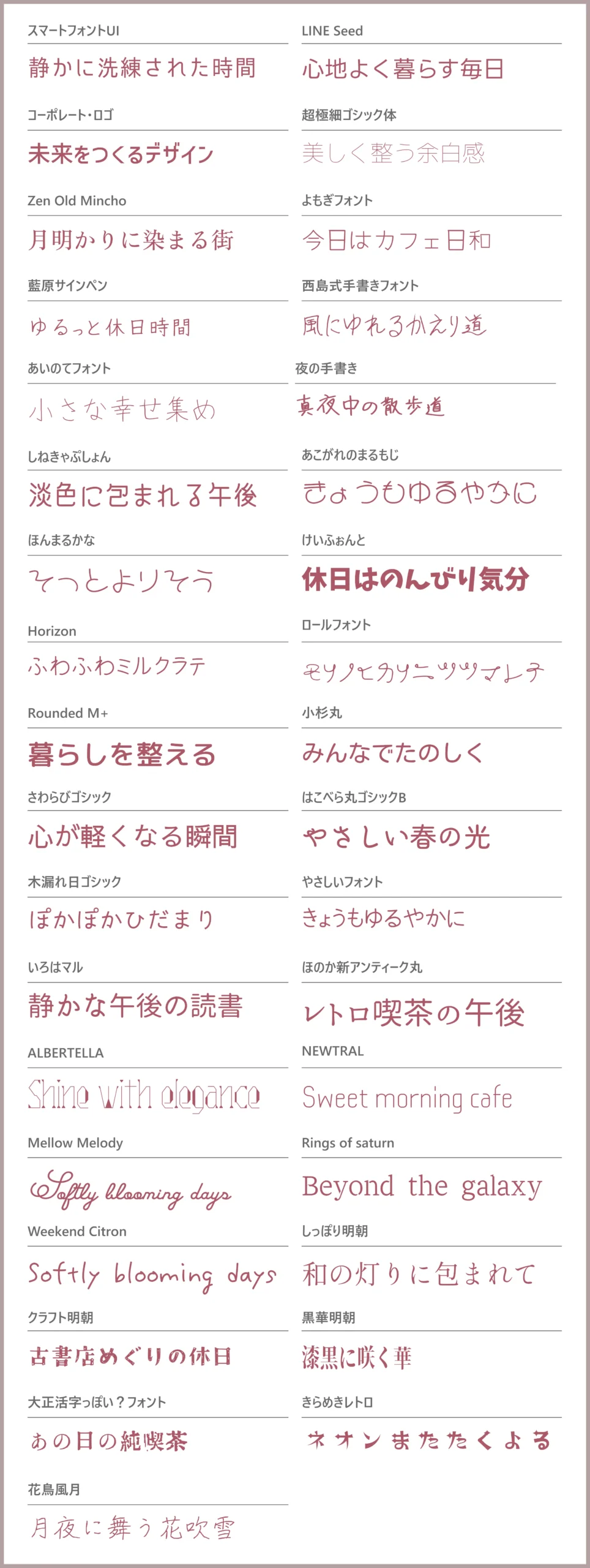
おしゃれフォントとは?
おしゃれフォントとは、単に文字を読むためだけではなく、“世界観や雰囲気を演出するため”に使われるデザイン性の高いフォントのことです。
同じ文章でも、フォントが変わるだけで「高級感」「かわいさ」「レトロ感」「近未来感」など、受ける印象は大きく変化します。
特に最近では、SNS投稿・動画サムネイル・ロゴ制作など、第一印象が重要なデザインでおしゃれフォントが多く活用されています。
ここでは、まず「おしゃれフォントとは何か」「普通のフォントと何が違うのか」をわかりやすく解説します。
おしゃれフォントの特徴
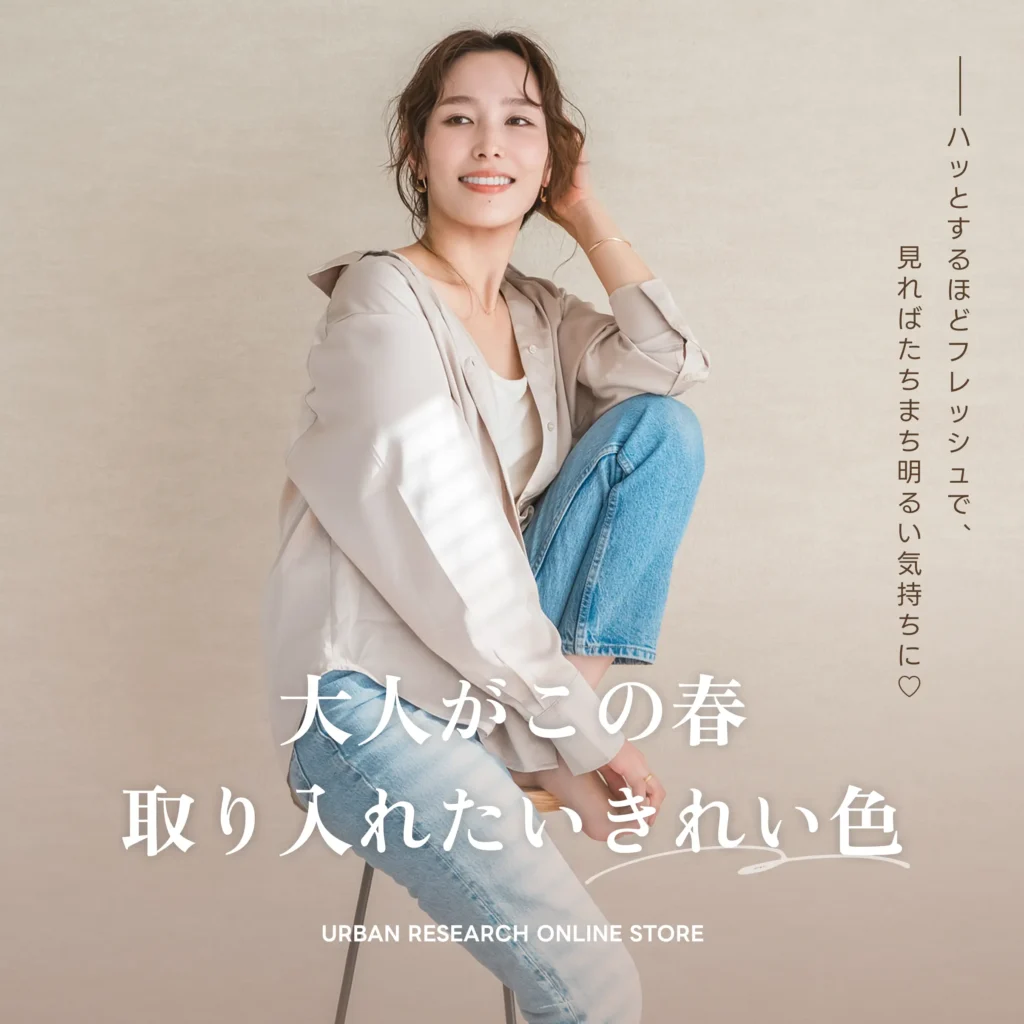
おしゃれフォントには、一般的な標準フォントにはない“デザイン性”があります。
例えば、線の太さに強弱があったり、文字の角が丸く設計されていたり、独特な余白バランスになっていたりと、文字そのものがデザインの一部として機能するのが特徴です。
特に以下のような特徴を持つフォントは、「おしゃれ」と感じられやすい傾向があります。
- 余白が美しい
- シルエットに個性がある
- 手書き感や筆記感がある
- ブランド感を演出しやすい
- 写真や動画と馴染みやすい
最近では、韓国風デザイン・Y2K・ミニマルデザインなど、トレンド系デザインでもフォントの重要性が高まっています。
普通のフォントとの違い
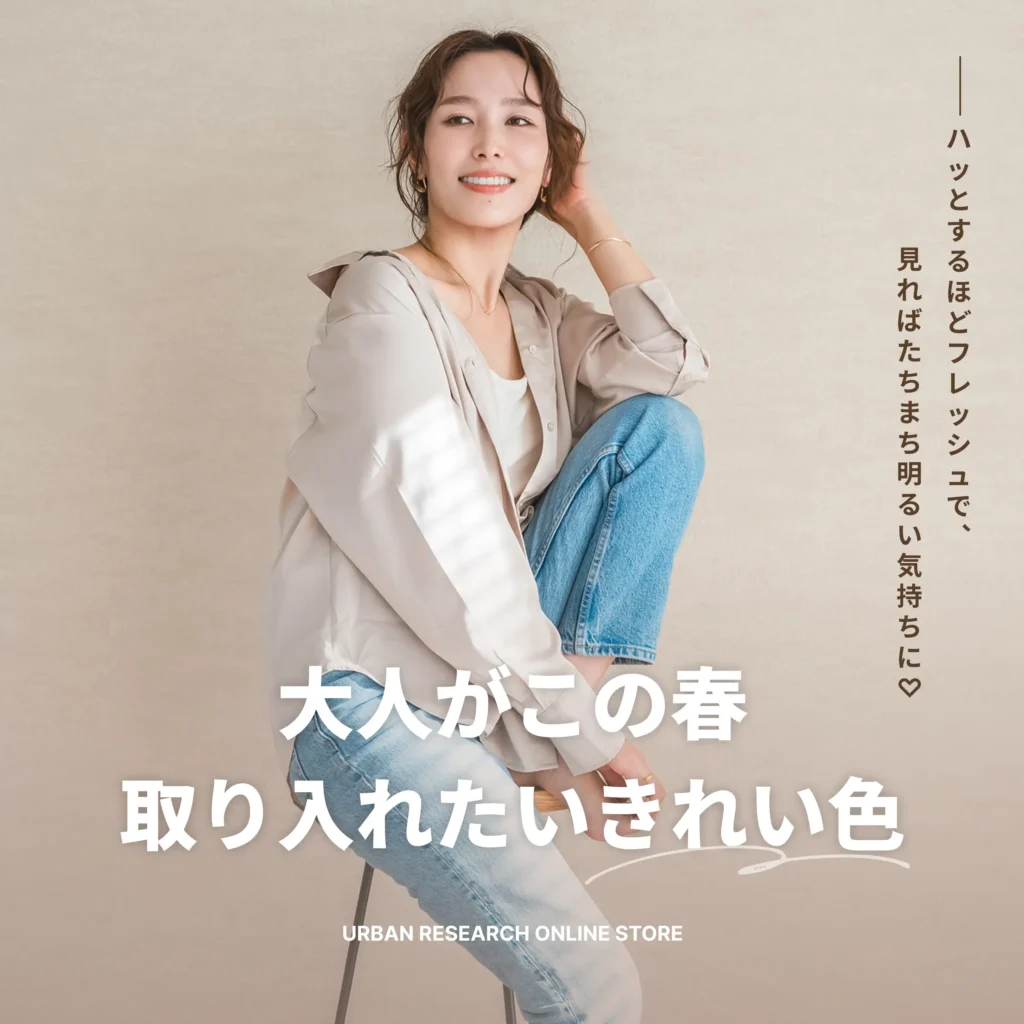
一般的なフォントは「読みやすさ」を重視して作られています。
一方、おしゃれフォントは“見せること”を目的として設計されているものが多く、文字自体がデザインのアクセントになります。
例えば、Wordの標準フォントは長文でも読みやすいように設計されていますが、おしゃれフォントはタイトルやロゴなど、印象を強く残したい場面で使われるケースが中心です。
そのため、
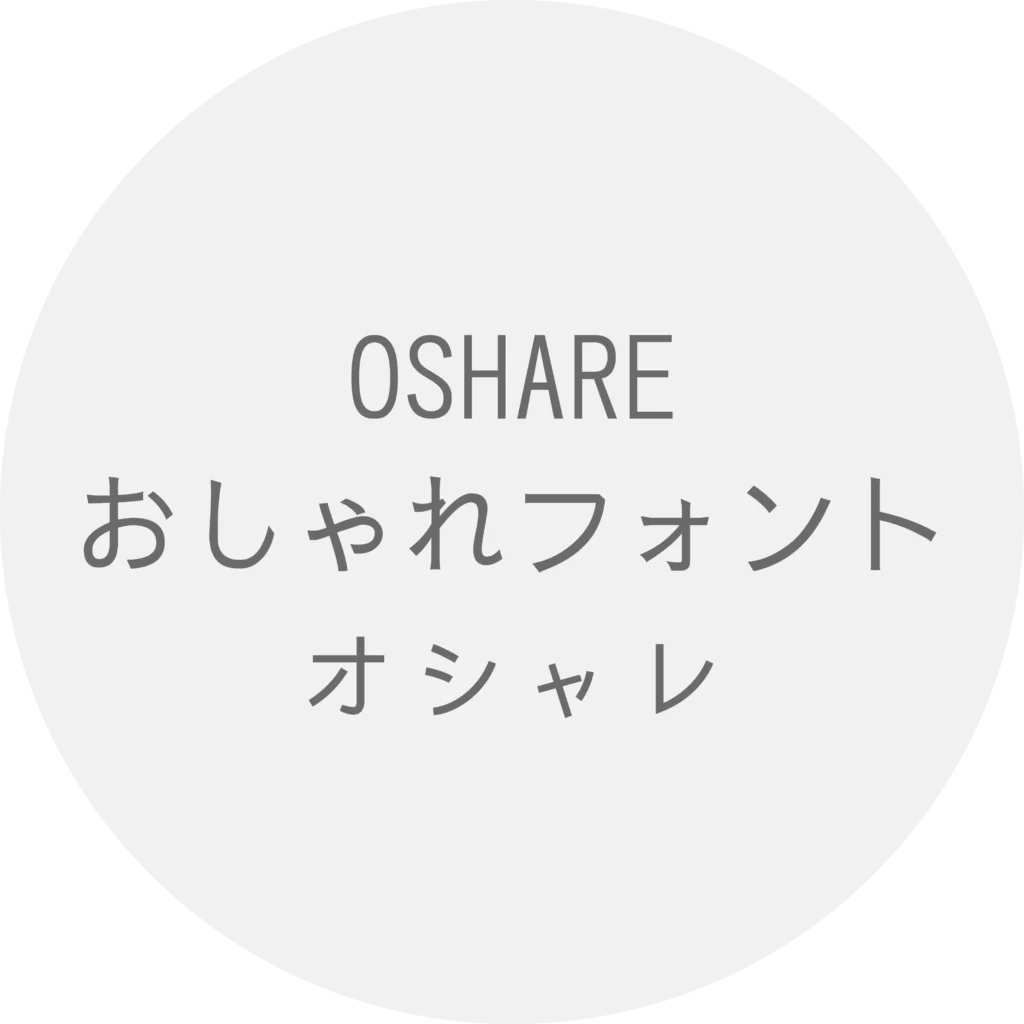
可読性重視
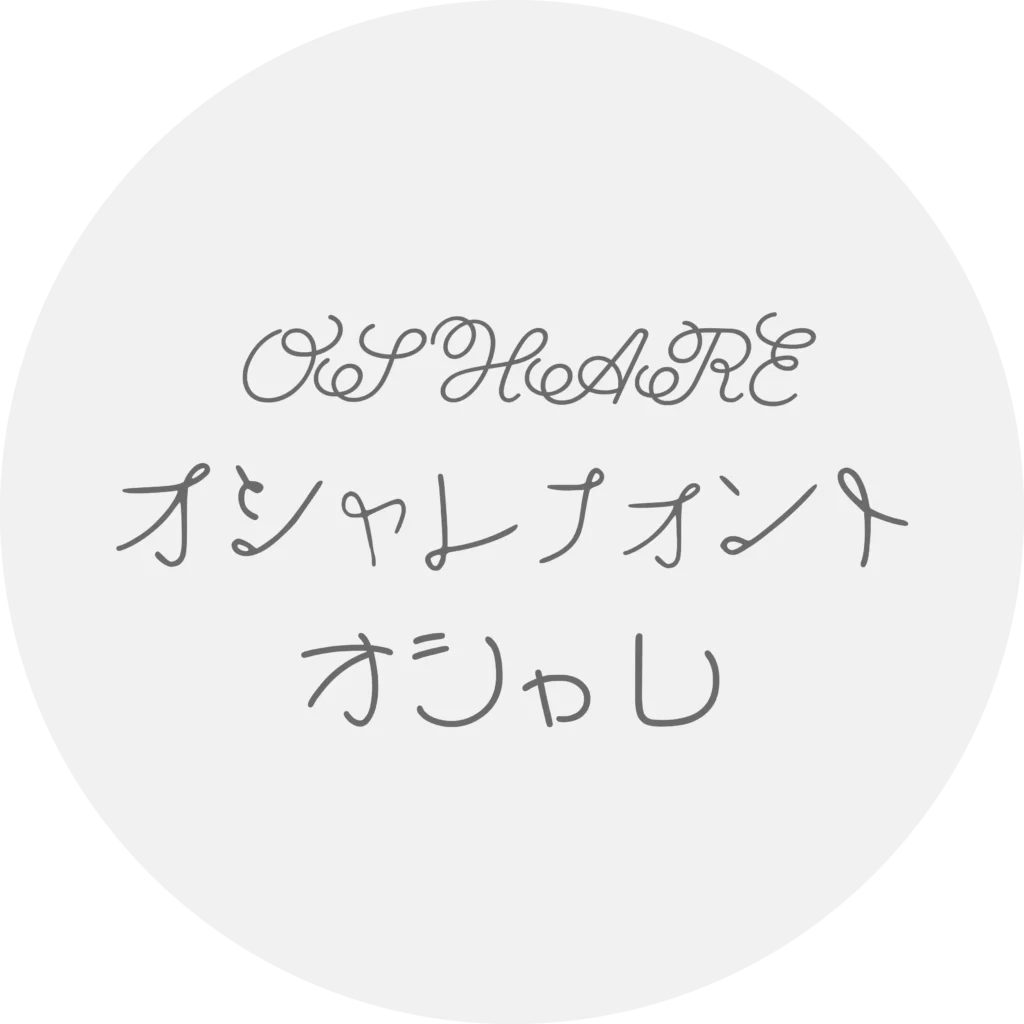
装飾性重視
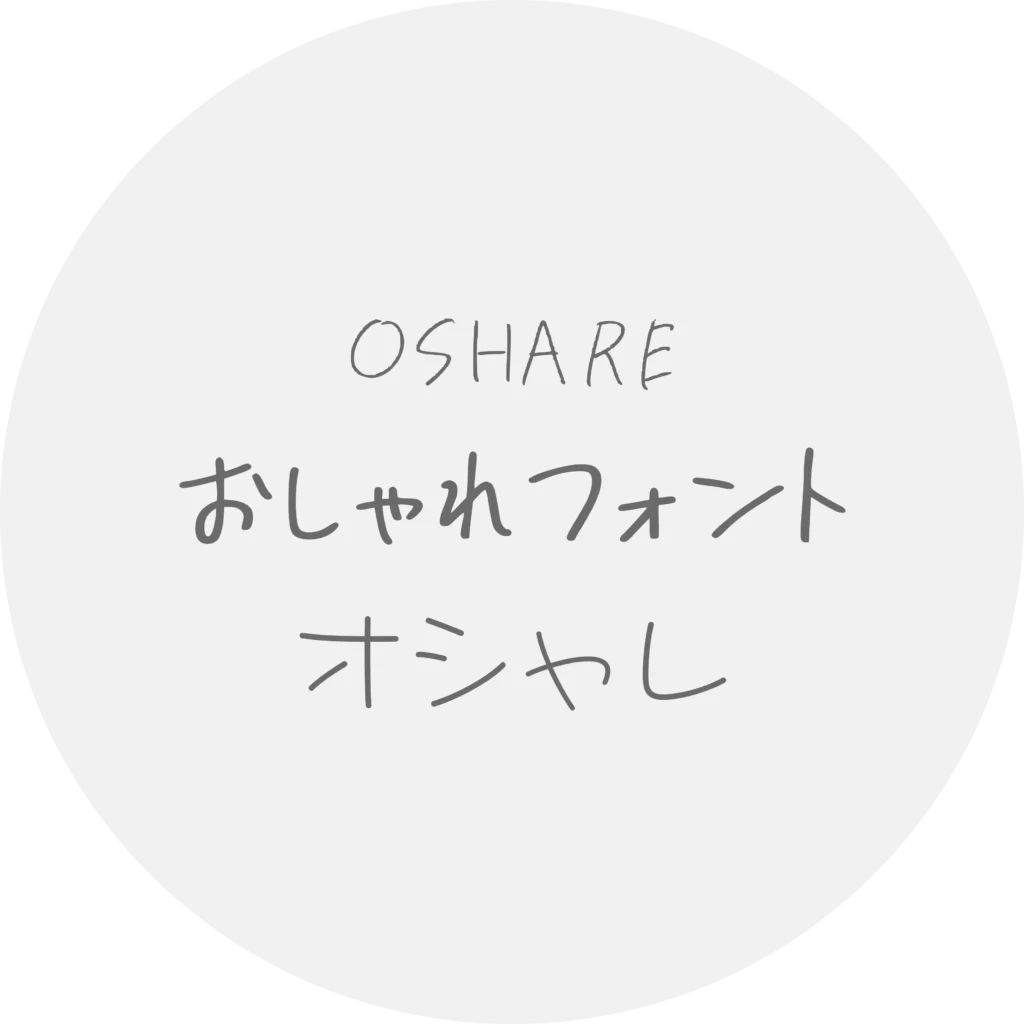
世界観重視
など、用途によって使い分けることが重要になります。
おしゃれフォントが使われる場面
おしゃれフォントは、さまざまなデザインシーンで活用されています。
特に近年はSNS・動画文化の広がりによって、“文字の見た目”そのものが重要視される場面が増えています。
例えば以下のような用途でよく使用されています。
- YouTube
- VTuber
- ロゴ制作
- カフェメニュー
- 同人誌
- バナー制作
フォント次第でクリック率や印象が変わるケースもあるため、デザインにこだわるならフォント選びは非常に重要です。
おしゃれフォントの選び方
おしゃれフォントは種類が非常に多く、なんとなくの雰囲気だけで選んでしまうと、デザイン全体に統一感がなくなってしまうことがあります。
特に最近は、Instagram投稿・YouTubeサムネイル・ブログ・ロゴ制作など、“文字そのものがデザインの一部”として扱われる場面が増えており、フォント選びによって印象が大きく変わります。
例えば、同じ文章でも、
- 丸みのあるフォントなら「かわいい・親しみやすい」
- 明朝体なら「高級感・上品」
- 極太ゴシックなら「インパクト・力強さ」
など、受ける印象はまったく異なります。
また、おしゃれなフォントを選んでも、「用途に合っていない」「文字が読みにくい」「日本語が足りない」といった理由で使いづらく感じるケースも少なくありません。
そのため、おしゃれフォントを選ぶ際は、
- どんなデザインに使うのか
- どんな雰囲気を出したいのか
- 商用利用できるか
- 日本語対応しているか
などを事前に確認することが重要です。
ここでは、失敗しにくいおしゃれフォントの選び方を、初心者にもわかりやすく解説します。
用途で選ぶ
まず最初に考えたいのが、「どこで使うフォントなのか」です。
同じ“おしゃれフォント”でも、ロゴ向け・SNS向け・動画向けでは、求められるデザインが大きく異なります。
例えば、YouTubeサムネイルでは「遠くからでも読める視認性」が重要ですが、カフェメニューでは「世界観や柔らかい雰囲気」が重視されます。
用途に合わないフォントを選んでしまうと、デザイン全体がチグハグに見えてしまうこともあるため、まずは使用シーンを明確にするのがおすすめです。
ロゴ制作向け
ロゴでは、“文字そのもののシルエット”が重要になります。
そのため、
- 個性的
- 高級感がある
- 余白が美しい
- シンプルでも印象に残る
といった特徴を持つフォントが人気です。
特に美容系ブランドやカフェロゴでは、ミニマル系・細字系フォントがよく使われています。
おすすめ系統:
- モダンゴシック
- 明朝体
- 英字筆記体
SNS投稿向け
InstagramやPinterestなどのSNSでは、写真との馴染みやすさが重要です。
最近は、
- 韓国風
- 淡色
- ナチュラル
- 手書き感
のあるフォントが人気で、やわらかくおしゃれな雰囲気を演出しやすい傾向があります。
また、スマホ表示でも読みやすい太さを選ぶことも重要です。
おすすめ系統:
- 手書き風
- 丸文字
- ナチュラル系フォント
動画サムネイル向け
YouTubeサムネイルでは、“一瞬で読めること”が非常に重要です。
そのため、
- 太字
- 視認性が高い
- インパクトが強い
フォントがよく使われます。
特にゲーム実況やVTuber系では、極太ゴシックやデザイン性の高いフォントが人気です。
おすすめ系統:
- 極太ゴシック
- インパクト系
- デザイン書体
ブログ・Webサイト向け
ブログやWebサイトでは、長時間読んでも疲れにくいフォントが重要です。
おしゃれさだけを優先してしまうと、可読性が下がり読みにくくなるケースもあるため、バランスが大切です。
最近では、
- 丸ゴシック
- ナチュラル系
- シンプルゴシック
など、柔らかさと読みやすさを両立したフォントが人気です。
おすすめ系統:
- 丸ゴシック
- シンプルゴシック
- やさしいデザイン書体
名刺・ショップカード向け
名刺やショップカードでは、シンプルで上品なフォントが人気です。
特に、
- ミニマル
- 高級感
- 洗練された雰囲気
を意識すると、統一感のあるデザインに仕上がりやすくなります。
美容室・ネイル・カフェ系では、細字フォントや英字フォントもよく使われています。
おすすめ系統:
- 明朝体
- 細字ゴシック
- 英字筆記体
フォントの雰囲気で選ぶ
フォントには、それぞれ異なる“雰囲気”があります。
同じ文章でも、フォントを変えるだけで「かわいい」「高級感がある」「レトロっぽい」など、デザイン全体の印象が大きく変わります。
そのため、作りたい世界観に合わせてフォントを選ぶことが重要です。
丸文字・丸ゴシック
- かわいい
- やさしい
- 親しみやすい
女性向けデザインやブログとの相性が良く、柔らかい印象を作れます。
韓国風・ナチュラル
- ミニマル
- やさしい雰囲気
- 抜け感
InstagramやVlog風デザイン、韓国カフェ風バナー、女性向けSNS投稿などに人気です。
手書き風
- ナチュラル
- カフェ風
- SNS向け
Instagram投稿や韓国風デザインとの相性が良い人気ジャンルです。
レトロ系